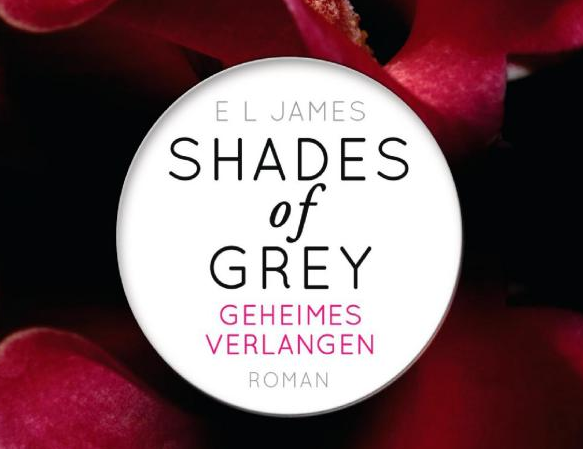
Schrift(ten) von Shades of Gray
Welche Schriften wurden für den Buchtitel von "Shades of Gray" verwendet?
wow das ging ja schnell! die Schrift ist super für das was  ich machen will.
Na, wenn die Schrift mal nicht nur wegen des Namens für Shades of Gray verwendet wurde, „Treibſand“ passt ja thematisch irgendwie ;-)
ein kleiner Spass für Freunde... aus der Titel wird leicht geändert. Die ganzen Zusammenhänge hier zu erklären wäre zu viel. Etwas so. (Ich hoffe die Augen der Profis hier ertragen die unpräzise Arbeit ist ja auch nur ein Hobby von mir für Kritik bin ich natürlich immer offen.
Ich habe eine ähnliche Frage, der "GREY-Bleistift" aus'm Film; wer ihn gesehen hat weiß bestimmt, was ich meine. Habt ihr da Tipps, was die Schrift angeht?